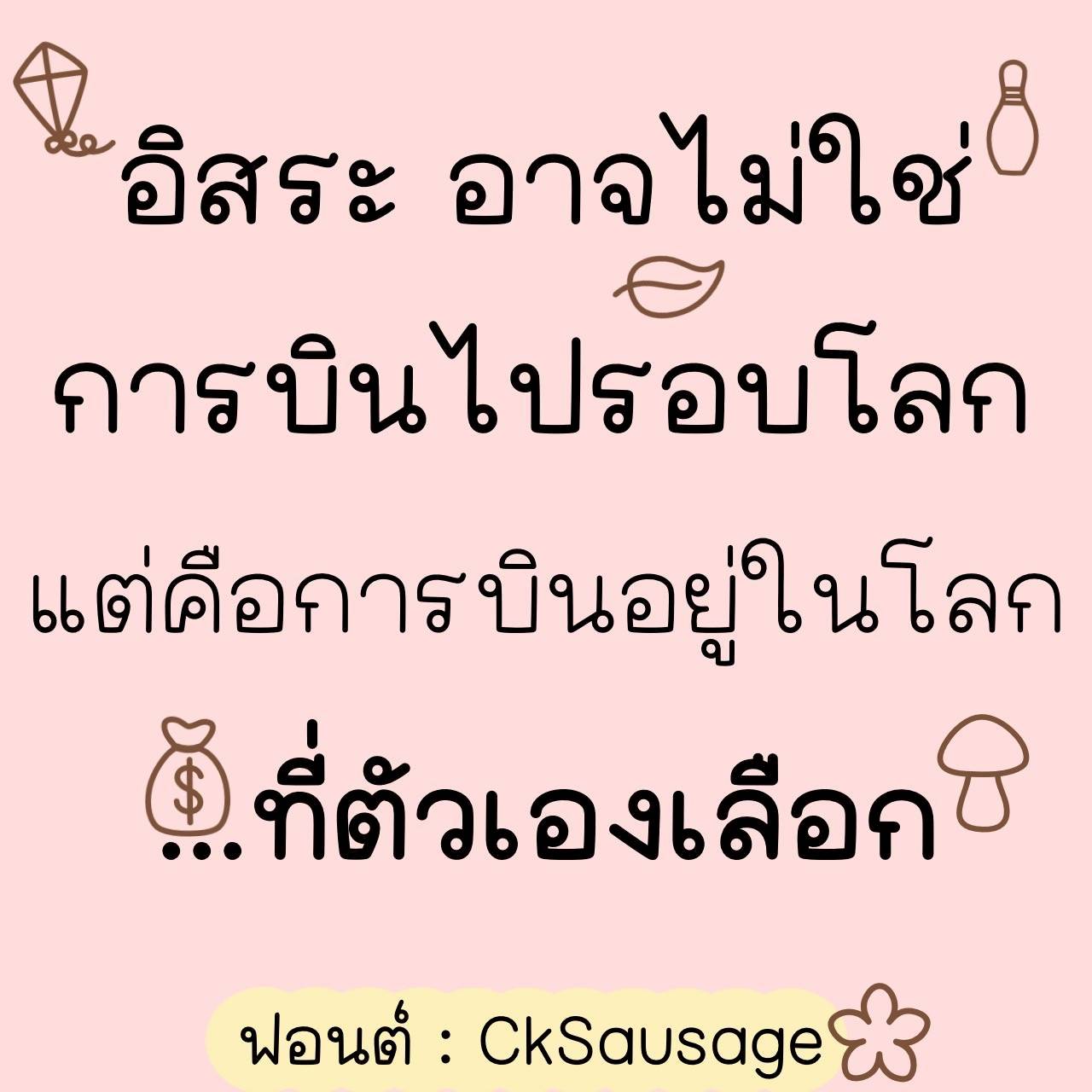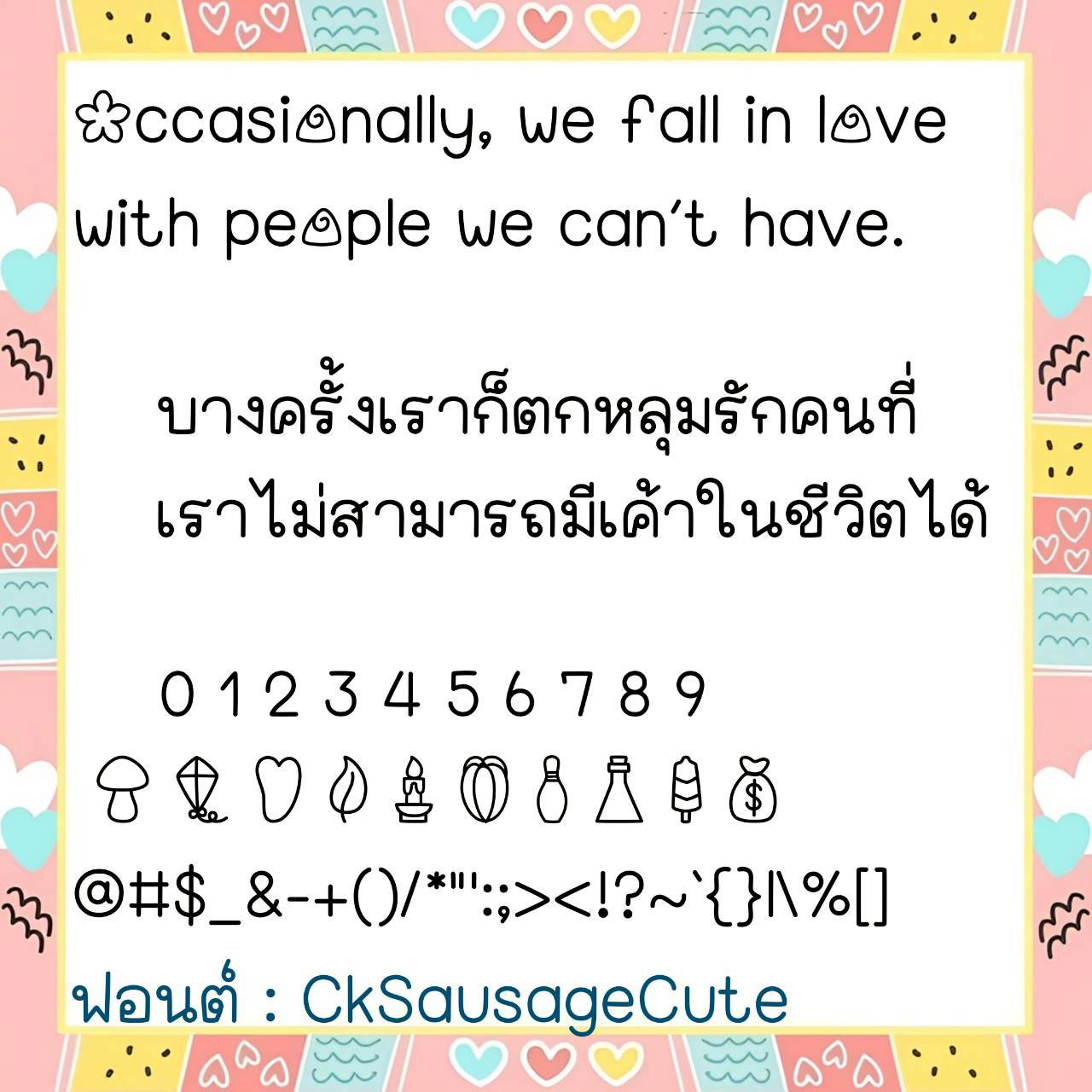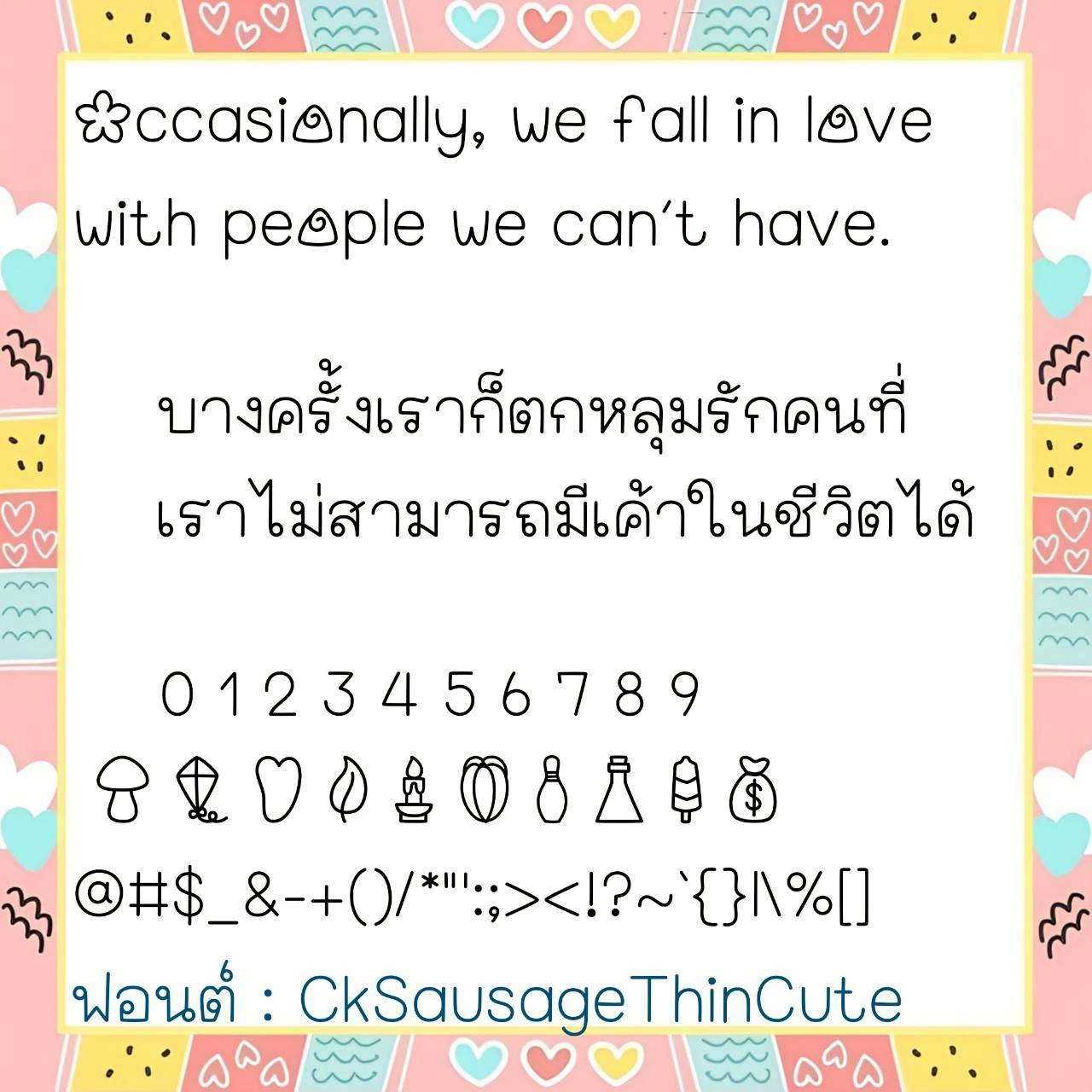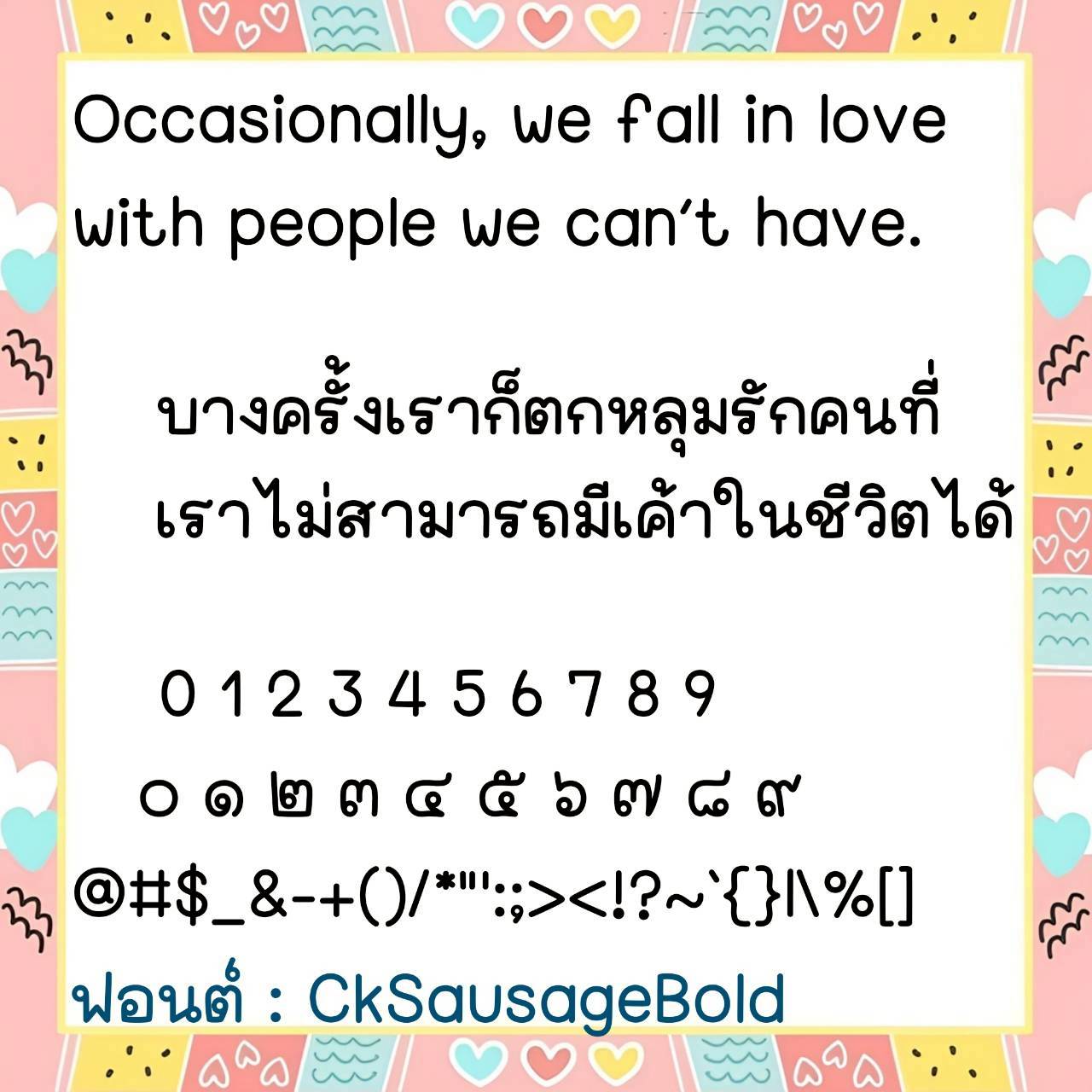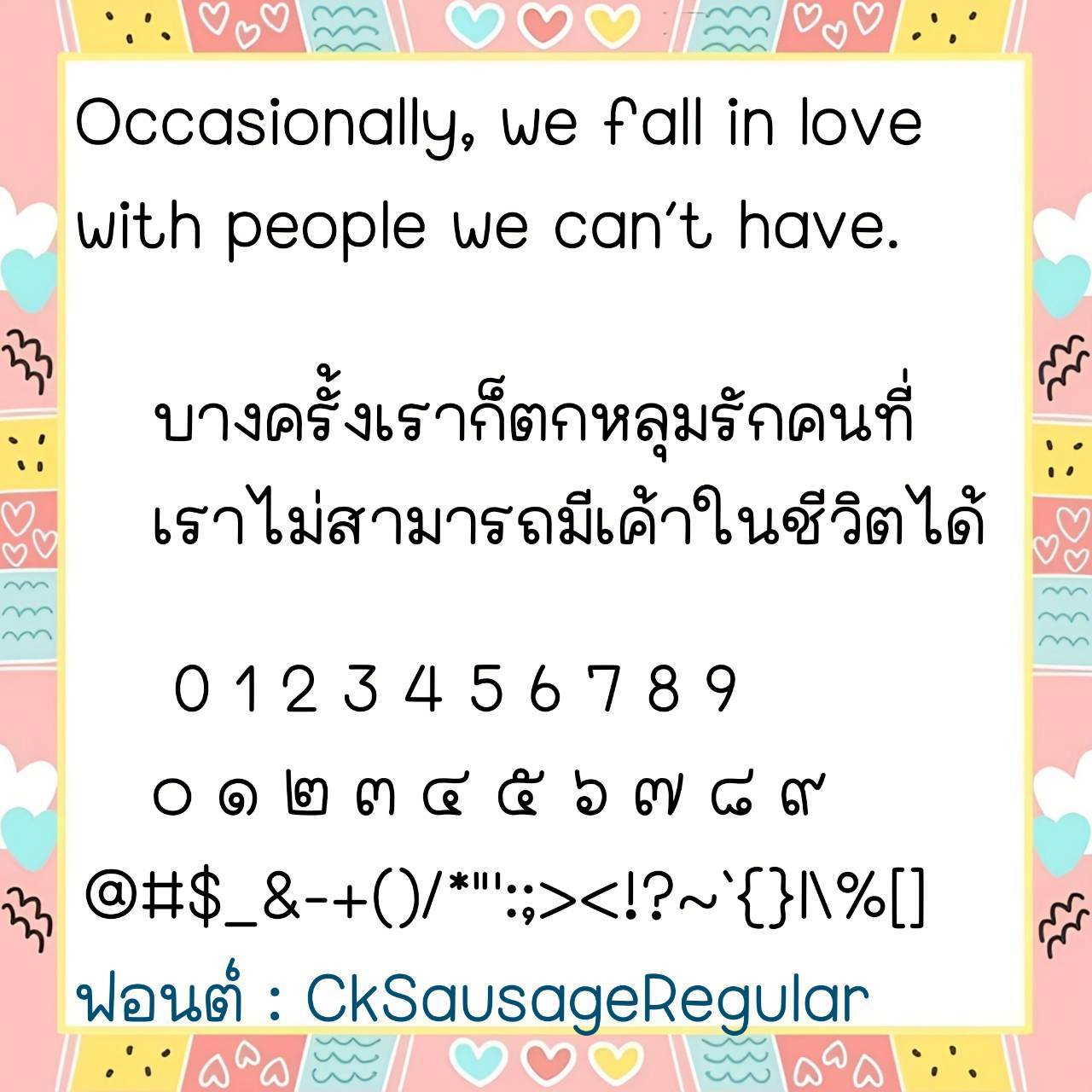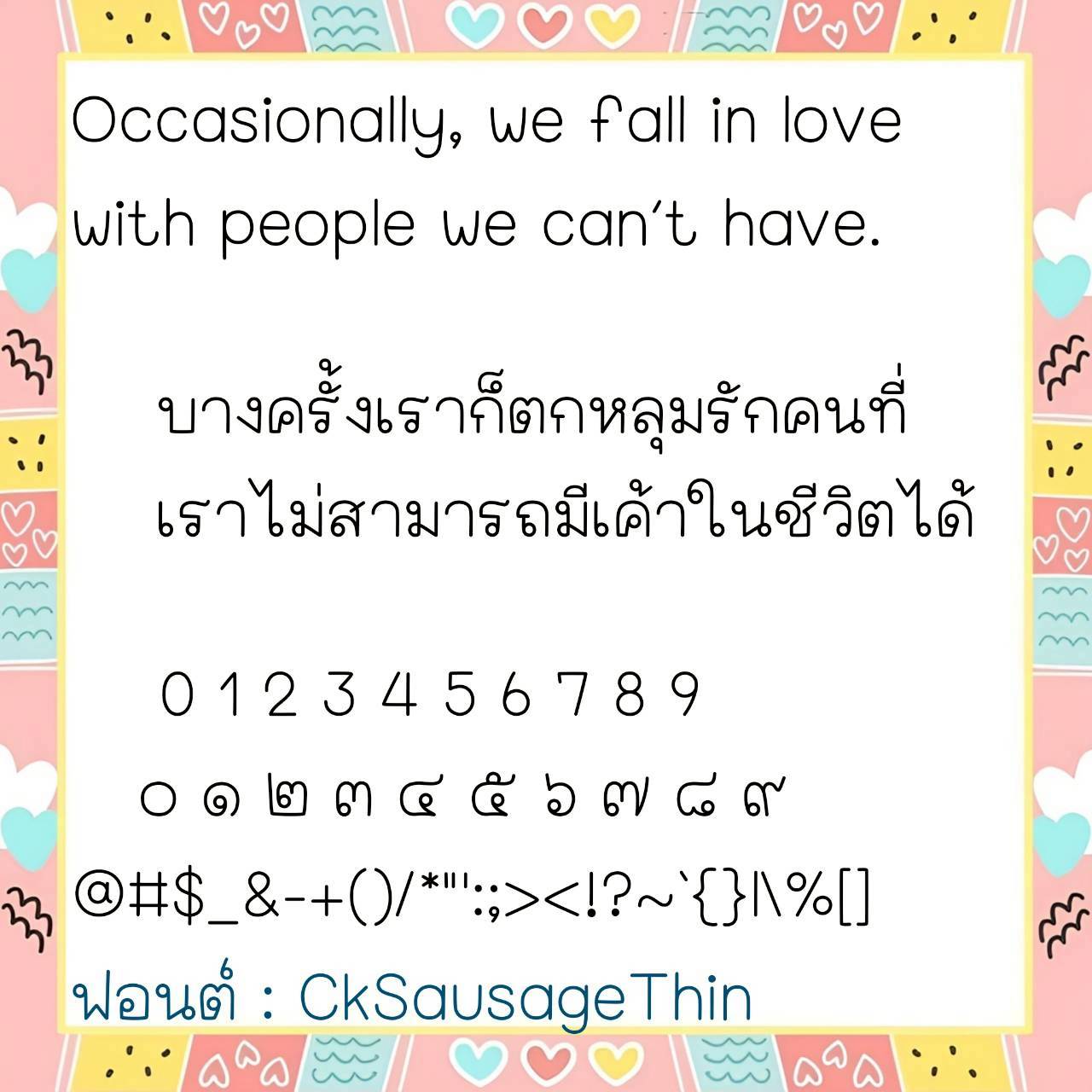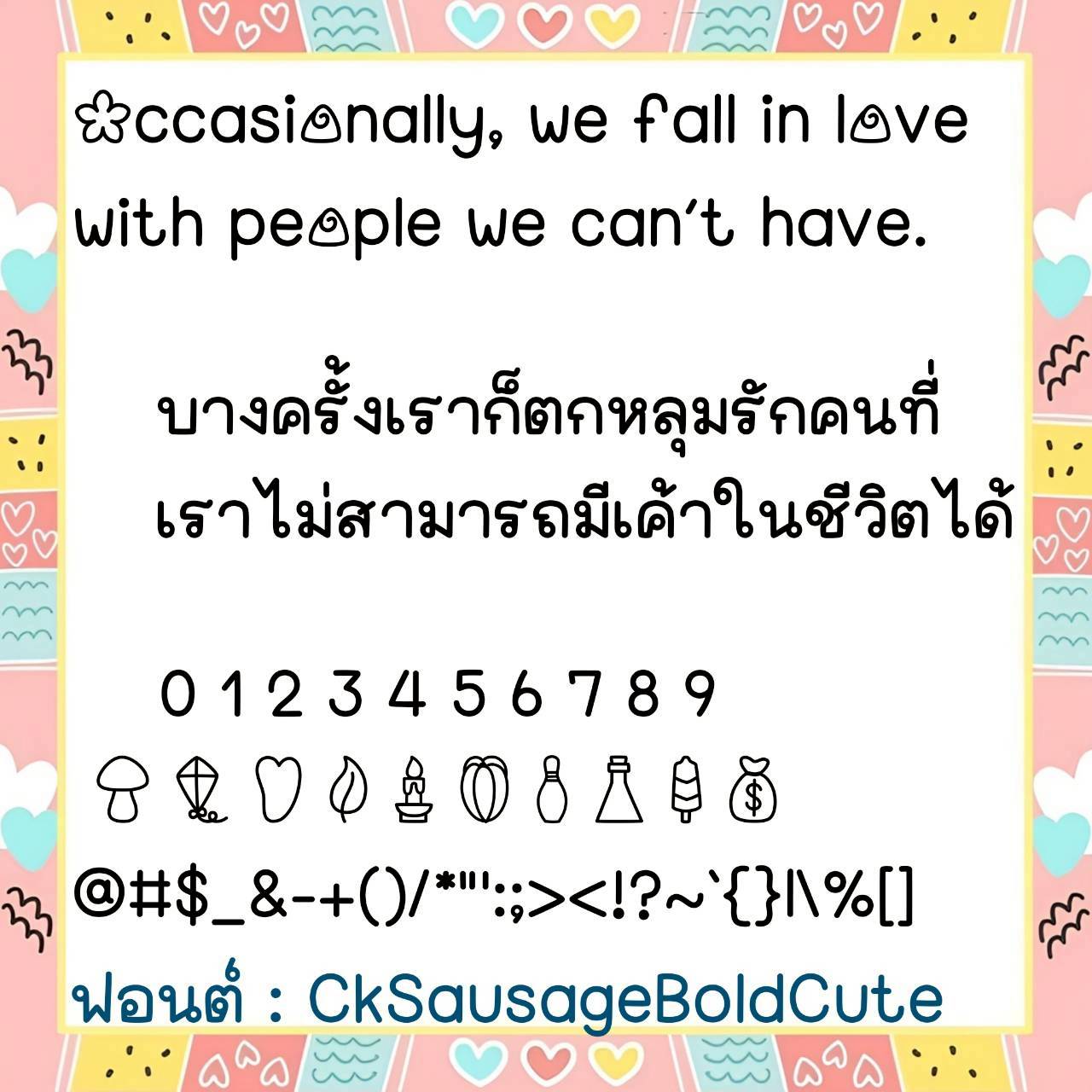
Font CkSausage
ชื่อสินค้า : Font CkSausage 💙
🔸 ฟอนต์ลายมือแนวเรียบร้อย ตัวอ้วน แต่มีความน่ารักเป็นระเบียบ เน้นอ่านง่ายสบายตา และยังมีไฟล์อิโมจิน่ารักๆที่ใช้แทนเลขไทยให้ด้วยค่ะ 🥰💙
🔹 A neat, chubby handwritten font that’s cute and organized, emphasizing readability and a comfortable viewing experience. It also includes cute emoji files to replace Thai numerals. 🥰💙